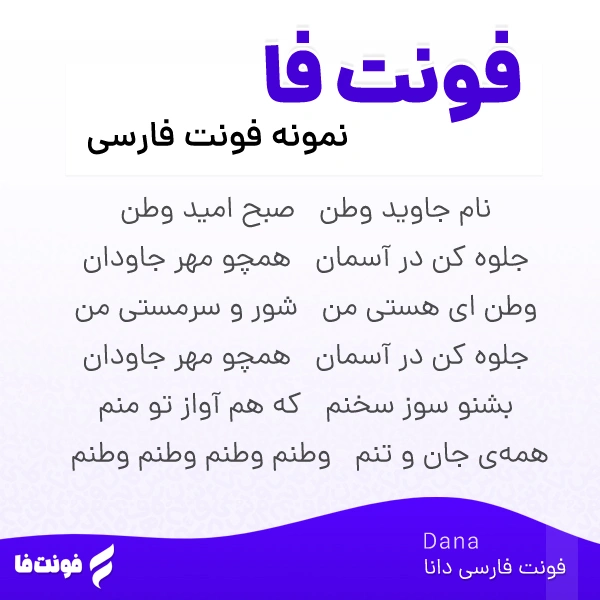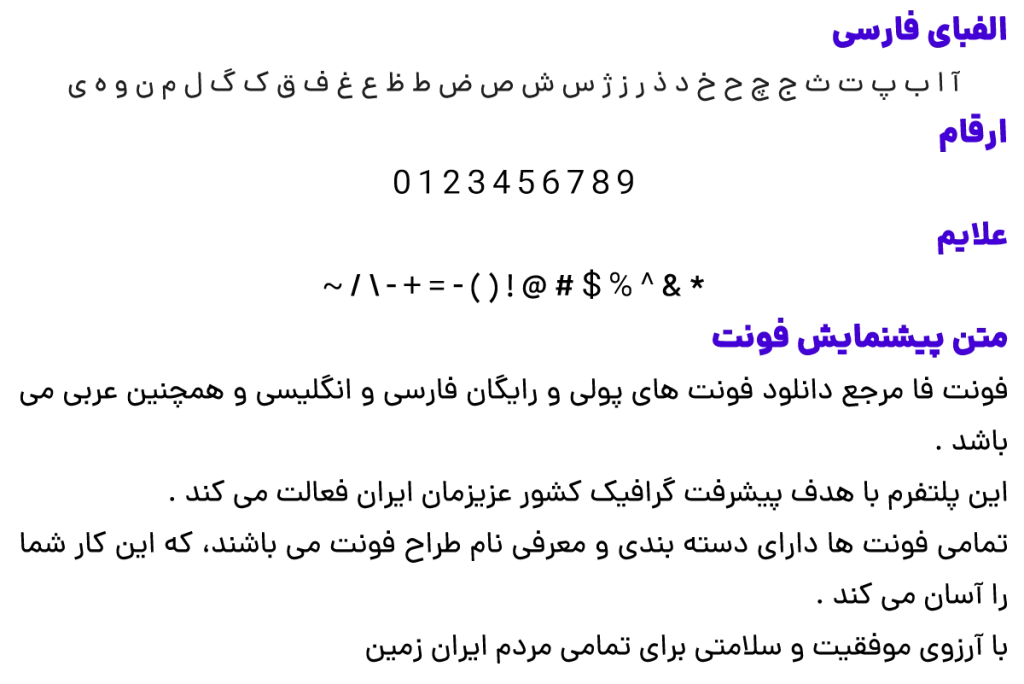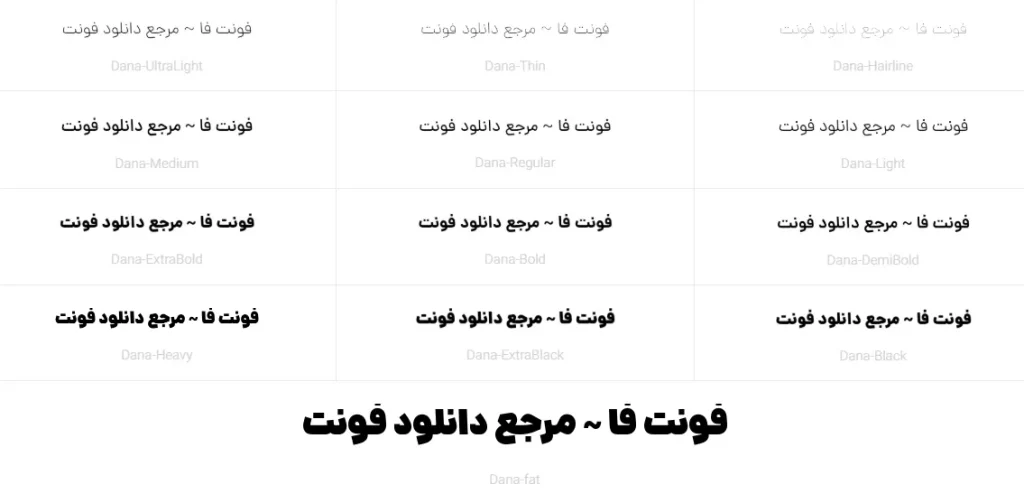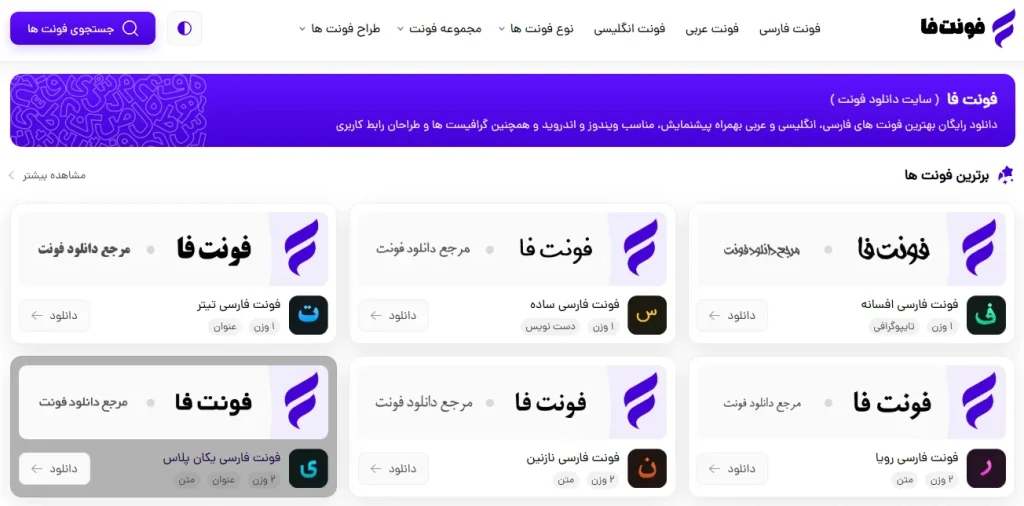
پیشنمایش فونت دانا
فونت فارسی دانا - Dana
توضیحات و معرفی فونت دانا
فونت فارسی دانا ( Dana ) از مجموعه فونت های آزاد و پولی می باشد، همچنان نوع فونت طراحی وب و عنوان و متن و هندسی می باشد.
فونت شگفت انگیز و زیبای فوق توسط شهرزاد اکبری و مسلم ابراهیمی در سال 1398 طراحی و ساخته شده است.
همچنان فونت Dana در 14 وزن سنگین و پر رنگ و نیمه پر رنگ و فوق العاده سنگین و فوق العاده پررنگ و حروف سنگین و سبک و متوسط و معمولی و نازک و فوق سبک و وریبل و چاق و خیلی نازک است.
در لیست زیر می توانید وزن های این فونت شگفت انگیز و زیبا را ببینید.
1. Dana Black
2. Dana Bold
3. Dana DemiBold
4. Dana ExtraBlack
5. Dana ExtraBold
6. Dana Heavy
7. Dana Light
8. Dana Medium
9. Dana Regular
10. Dana Thin
11. Dana UltraLight
12. Dana Variable
13. Dana Fat
14. Dana HireLine
در تصویر زیر تمامی وزن های فونت دانا را می توانید مشاهده کنید…
وزن های فونت دانا
شعر فارسی با حال و هوای وطن، نوشته شده با این تایپ فیس، در عکس زیر قابل مشاهده است.
پیشنمایش فونت دانا
توضیحات زیر علاقه شما را به این فونت چند برابر می کند…
این تایپ فیس با ترکیب هندسه منظم و الهام از خط نسخ، ظاهری ساده، دقیق و در عین حال خوانا دارد. دانا در 14 وزن مختلف و همچنین بصورت وریبل فونت عرضه شده که امکان تغییر وزن و کشیدگی را فراهم می کند.
طراحی حساب شده نقطه ها و دندانه ها باعث افزایش نظم و وضوح در متن شده و همین موضوع آن را برای استفاده در متن‌های طولانی و محیط‌های دیجیتال بسیار کاربردی کرده است.
در تصویر زیر می توانید سایت فونت فا رو که با همین فونت طراحی شده رو ببینید…
سایت فونت فا با فونت دانا
همچنین فونت دانا علاوه بر فارسی از زبان هایی چون عربی، اردو و کردی پشتیبانی می کند و به دلیل تنوع وزنی و سادگی، انتخابی مناسب برای طراحی گرافیکی و تایپوگرافی مدرن و طراحی وب به شمار می آید.
فونتی که خیلی از وب سایت ها و اپلیکیشن های معروف نظیر تپسی، افق کوروش، هاست ایران، ازکی وام و … استفاده کرده اند.